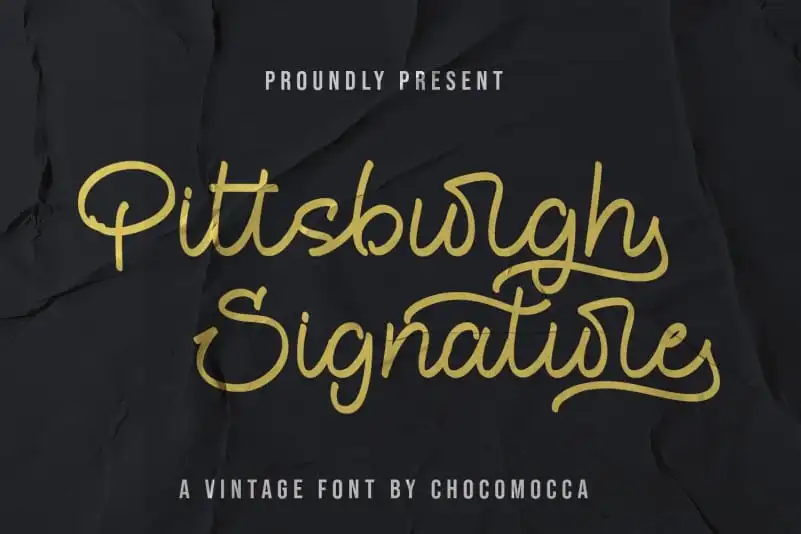
Pittsburght Signature Font – Download Grátis
A Pittsburght Signature Font é uma escolha perfeita para os designers que buscam algo natural e elegante no seu próximo projeto visual. Escrevendo casualmente, como se fosse digitado a mão com um pincel, esta fonte vem equipada para trazer a sua produção à vida de maneira única e imponente. Introduzida pela Hamilton, a Pittsburght Signature Font apresenta o famoso ‘Pittsburgh Signature’, uma tipografia de script vintage inspirada em estilos modernos e retro. Cada característica dessa fonte é cuidadosamente projetada para um efeito natural que complementará qualquer projeto gráfico. Perfumado com a essência da autenticidade, esta fonte irá brilhar em várias aplicações. Você pode usar-a em logotipos tradicionais, rótulos de embalagens, textos para camisetas e mais. O Pittsburght Signature Font está aqui para oferecer uma paleta de opções perfeita para projetos que exigem um toque autêntico e elegante. Com a sua aparência casual e o seu brilho único, esta fonte vai tornar cada projeto visual em que é utilizada algo especial. Sua versatilidade irá certamente preencher uma lacuna na sua ferramenta de recursos gráficos, garantindo que sempre esteja pronto para criar a obra-prima perfeita.